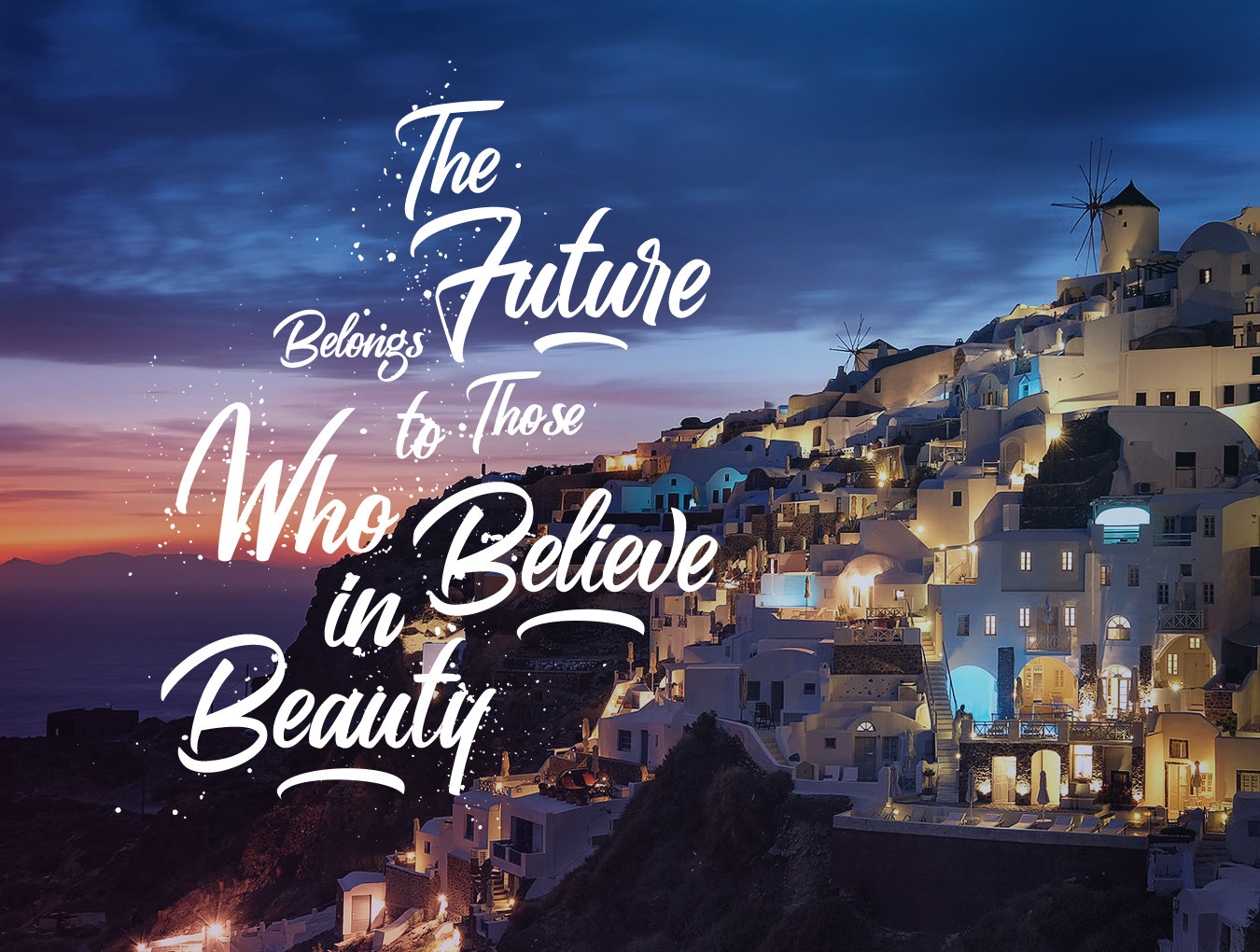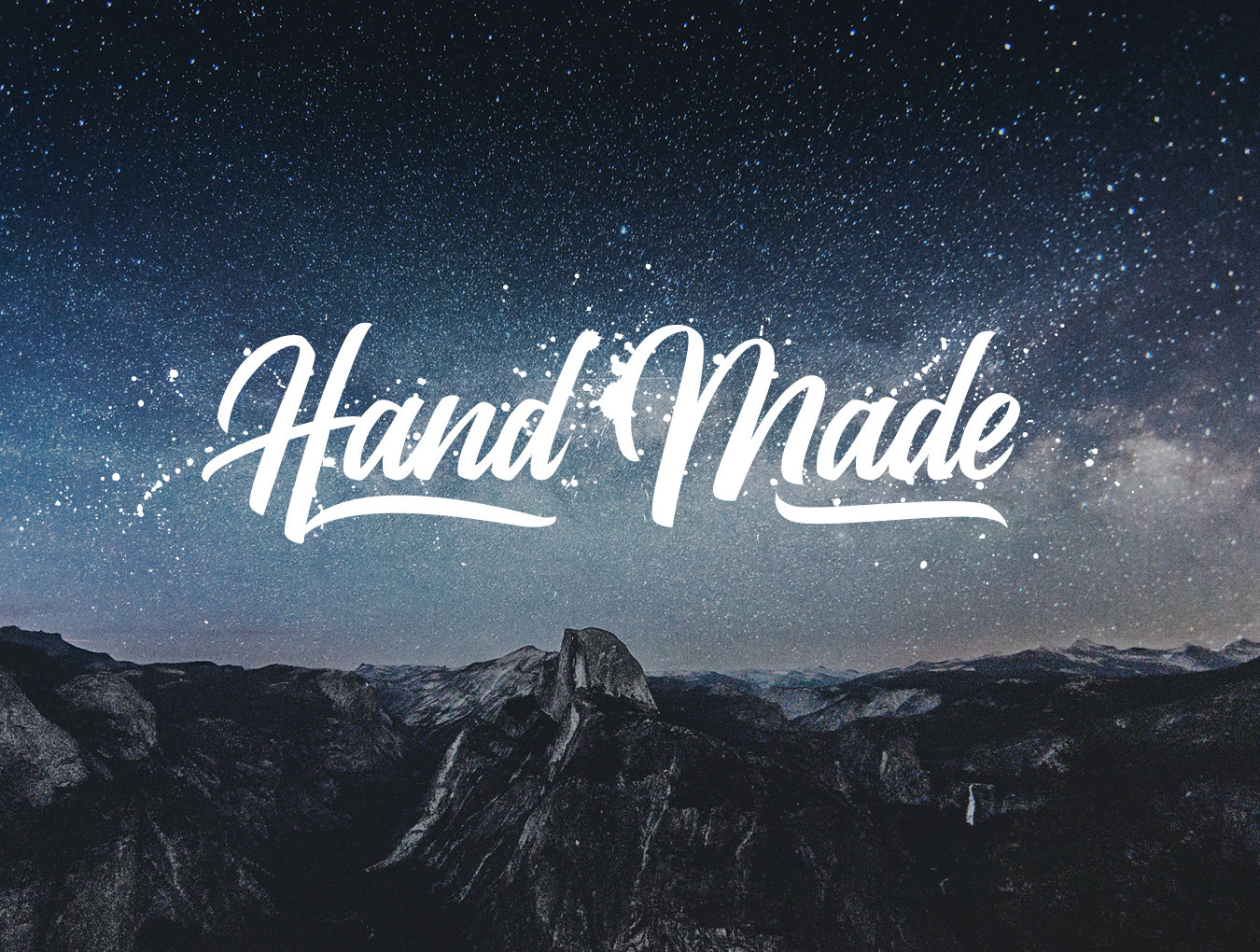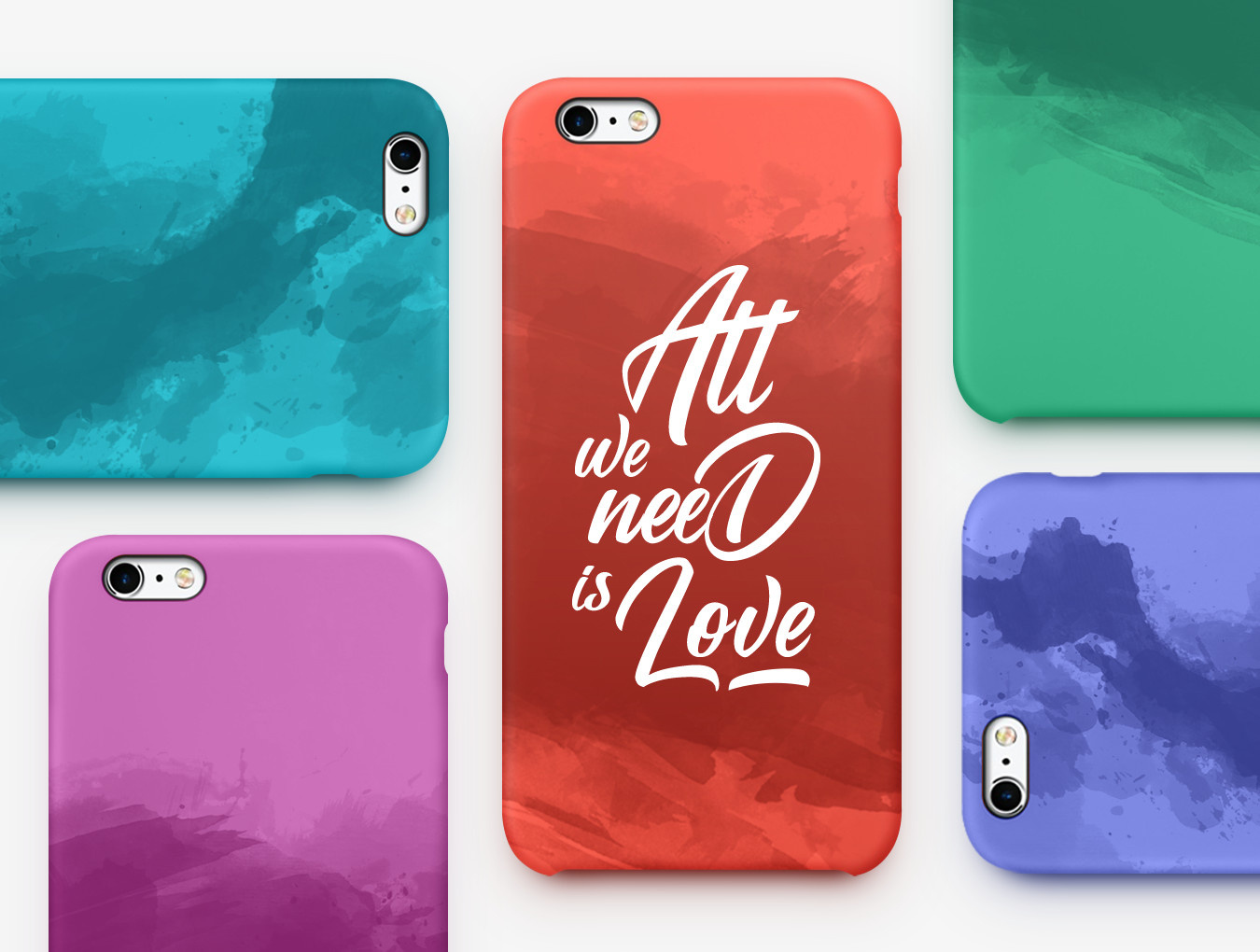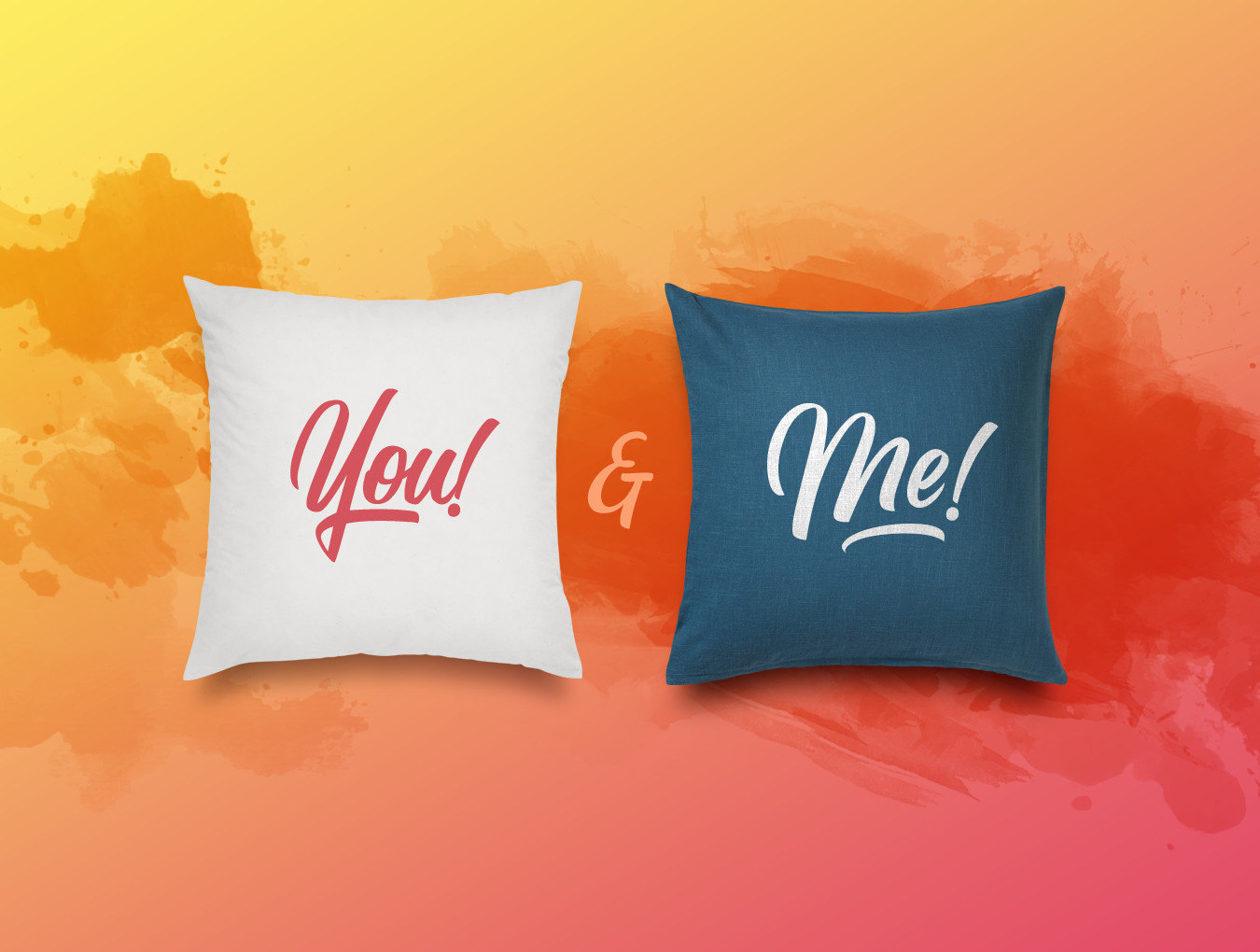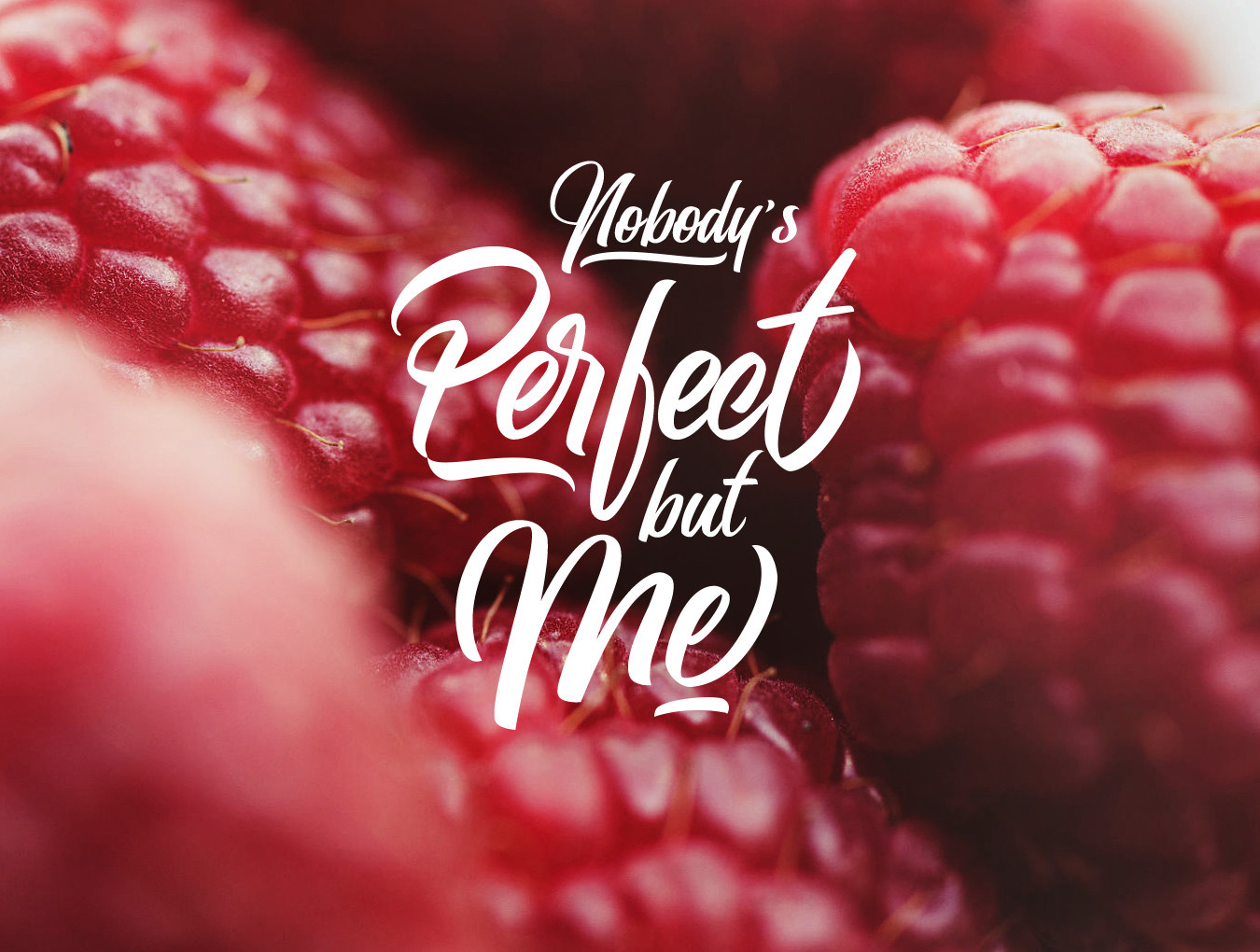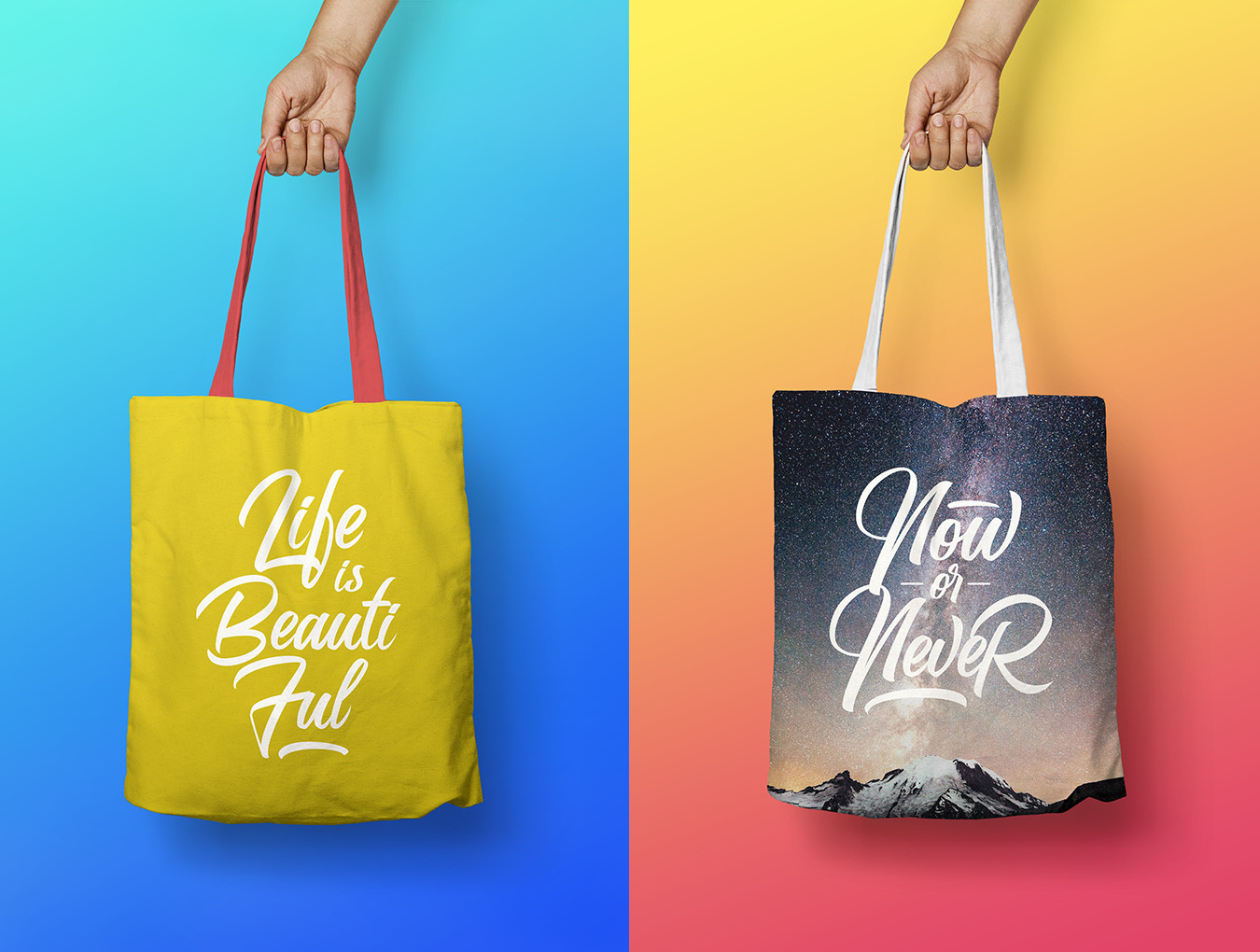
Perfect brush font just for you, Kelium
Kelium是一种带有画笔风格的手绘字体,非常适合后期,服装设计,标题,标识,海报,卡片等。对于拥有opentype功能软件的人来说:通过打开'Stylistic Alternates'和'可以访问替代品Photoshop的“角色”面板中的“连接”按钮,或者通过任何带有字形面板的软件,例如Adobe Illustrator,Photoshop,Inkscape。